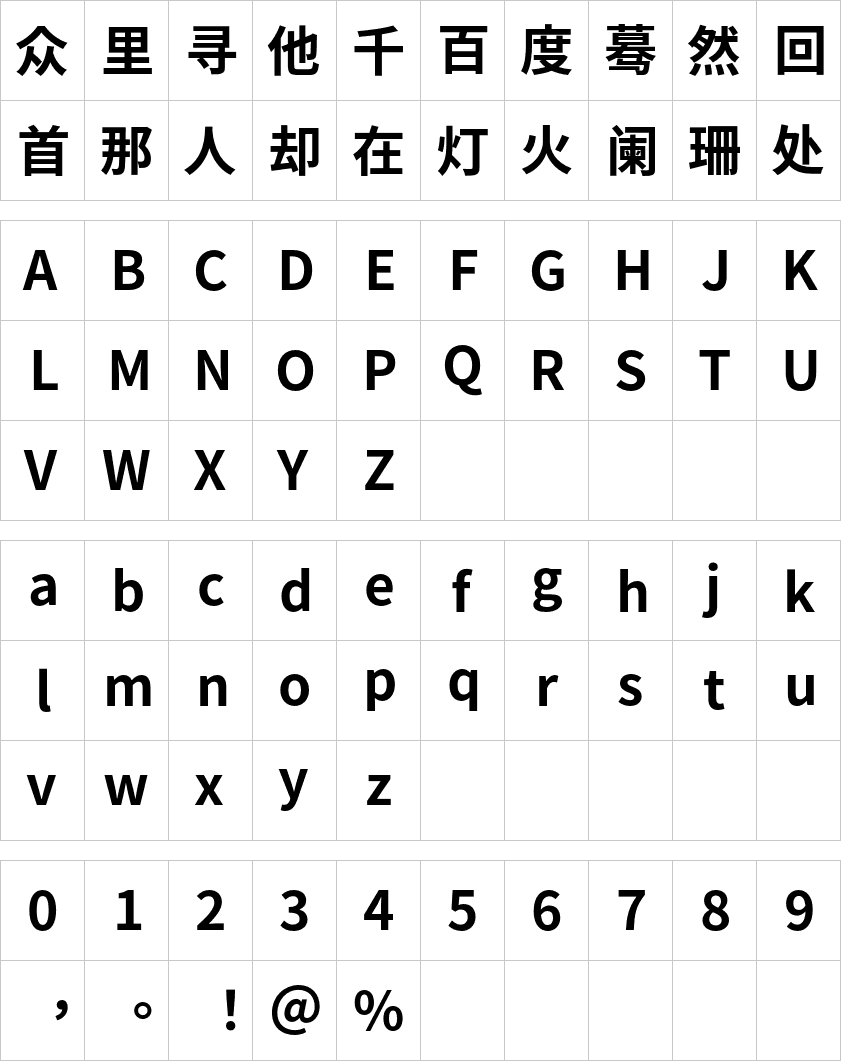
秋空黑体
A Chinese language font family project derived from Source Han Sans and integrated with Ideographic variation sequence.
一款基於思源黑體,同時整合異體字選擇器功能的中文印刷體風格字體家族專案。